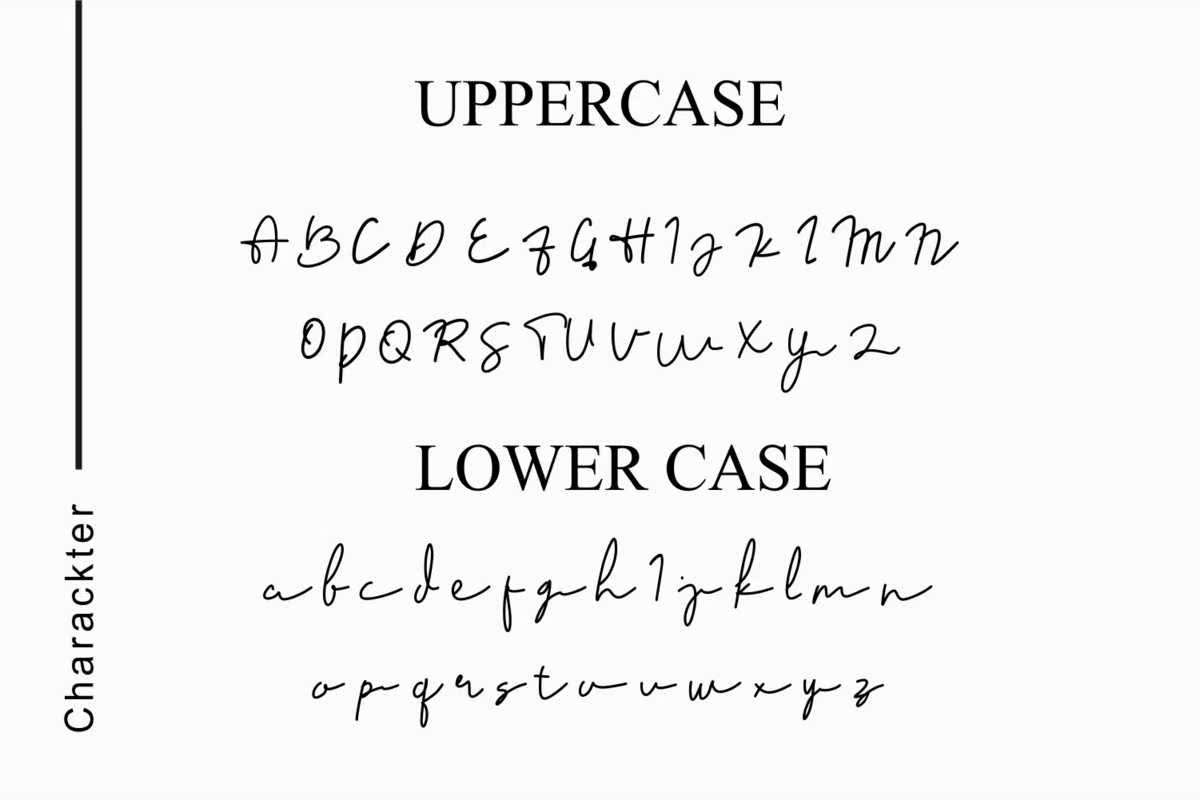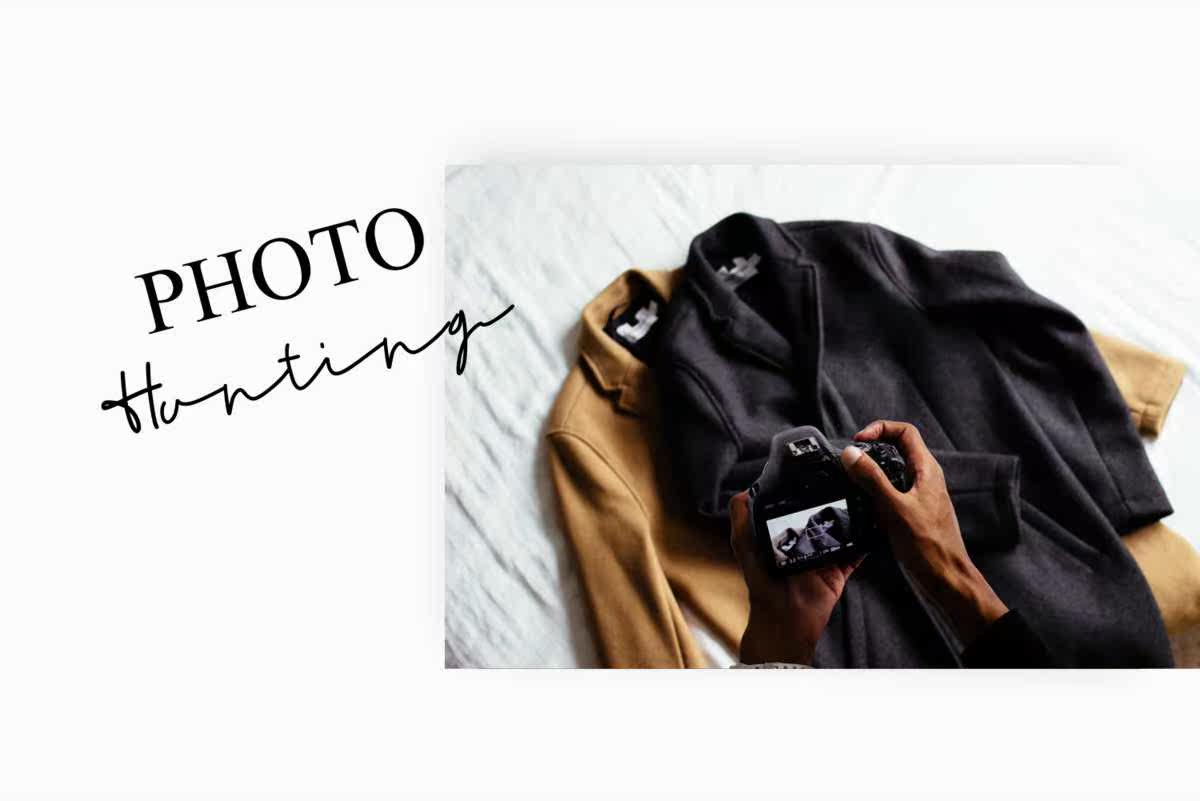
Ainsleys-Signature Contains是一个可用于多种类型的签名,此Fonts还配有一个PentypeFeature,例如可选的清洗连接。此Fonts将帮助您创建令人惊叹的产品,您可以在下面的链接中循环。Ainsleys-Signature Contains是一个可用于多种类型的签名,此Fonts还配有一个PentypeFeature,此字体将帮助您创建令人惊叹的产品,您可以在下面的链接中查看循环链接。